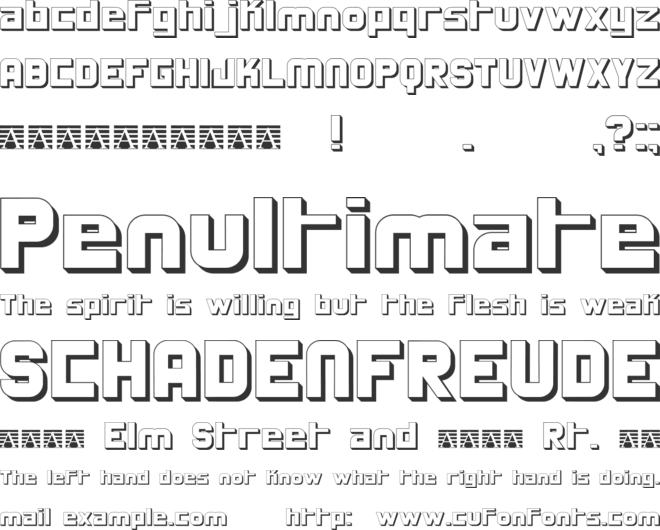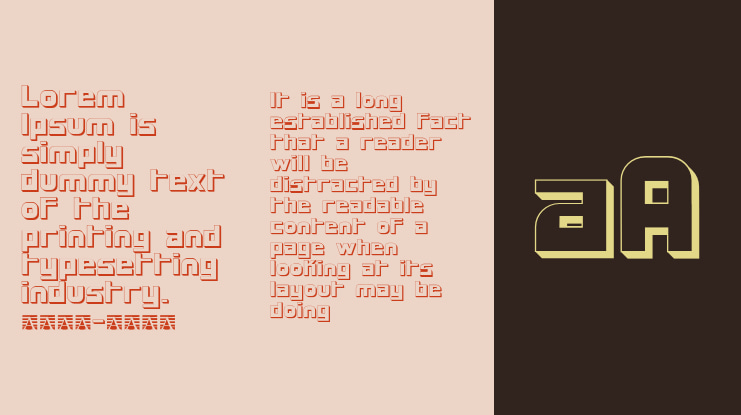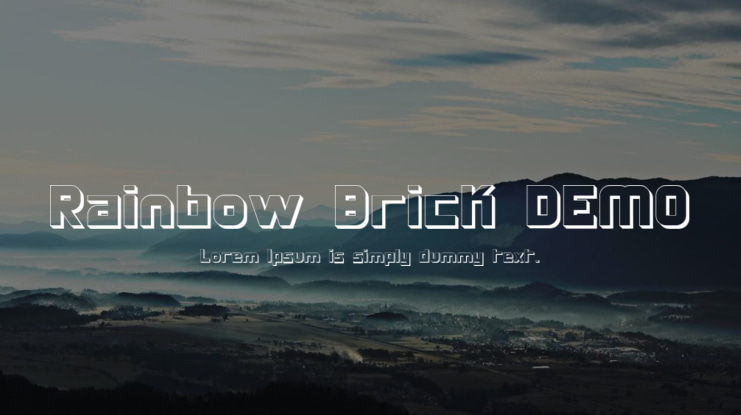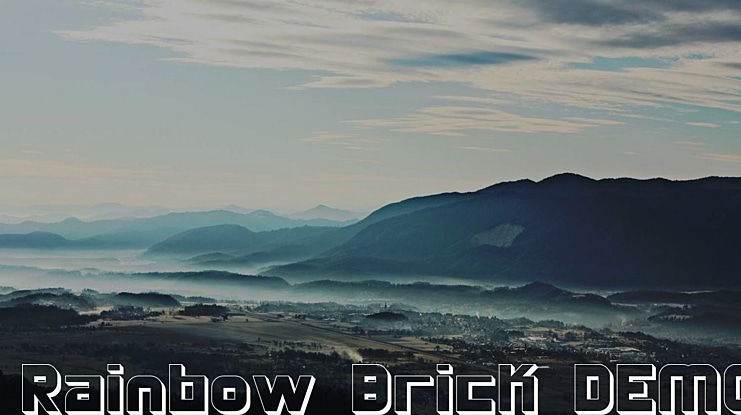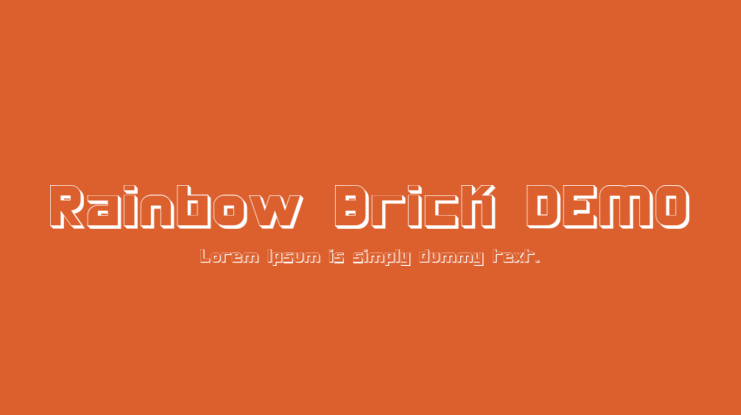
Rainbow Brick DEMO Font
P.A.Vannucci per Alphabet&Type® DIGITAL TYPEFACES
Dalla geometria chiaroscurale dell'elemento 2d, lo stile illustrativo in un font pregiato disponibile nel formato Open Type regular.